ざっくばらんに文字談義――砧書体制作所の片岡朗さんと木龍歩美さんをお招きして
FONTPLUSでは毎月第3水曜日に「FONTPLUS DAYセミナー」というオンラインイベントを開催しております。42回目の今回は、広告やポスターなどで20年間以上にわたり使われ続ける「丸明オールド」を生みだした砧書体制作所の書体デザイナー片岡朗さんと木龍歩美さんをお招きし、フォントの楽しさや可能性、未来など……ざっくばらんと題しながらもとても濃い談義となりました。ぜひ楽しんで見てください!
「水や空気と一緒でみんなが意識せず使っているフォントも実際には創っている人がいて、創る人の性格がでるからおもしろい」(片岡さん)。砧制作所の書体を生み出したのはどんな方々なのか……お二人の現在に至るまでをお話ししていただきました。
「砧書体制作所生みの親・片岡朗」の誕生ヒストリー
学生時代は夜間の学校に通っており、日中は仕事をしている人も多く、様々な職種の人と出会ったことで刺激を受けたそう。みんなで夢を語り、この頃から仕事に対する考えが深くなったのだとか。
その後店舗の看板等の装飾をしていたお父様から紹介された会社で文字と出会います。そこでは映画の看板やモーターショーの説明パネルの文字を書くような仕事を3年間行っていました。
そして広告業界へ転職。面接の際作品を見せてと言われたが用意しておらず、急遽紙と面相筆で文字を書いたところ採用されたそうです。文字に明朝体やゴシック体といった種類あることはここに入ってから知ったそう。「在職していた3年間は毎日残業三昧だったが、この経験が今のストイックさに繋がっている」と片岡さんはおっしゃいます。
その後はスタンダード通信社へ。デザイナーのアシスタントとして働きながら、当時開催されていた「第2回石井賞創作タイプフェイスコンテスト(1971年)」に応募し、見事第3位に選ばれました。その数年後に独立し、カタオカデザインワークスを設立。
お話を聞いていると、人との繋がりで今の自分があるのだなと改めて考えさせられますね。片岡さんの行動力と決断力も見習いたいです! 得意なことを見つけ、ストイックながらも自分自身が楽しみながら仕事をされている印象が魅力的でした。
代表作「丸明オールド」誕生秘話
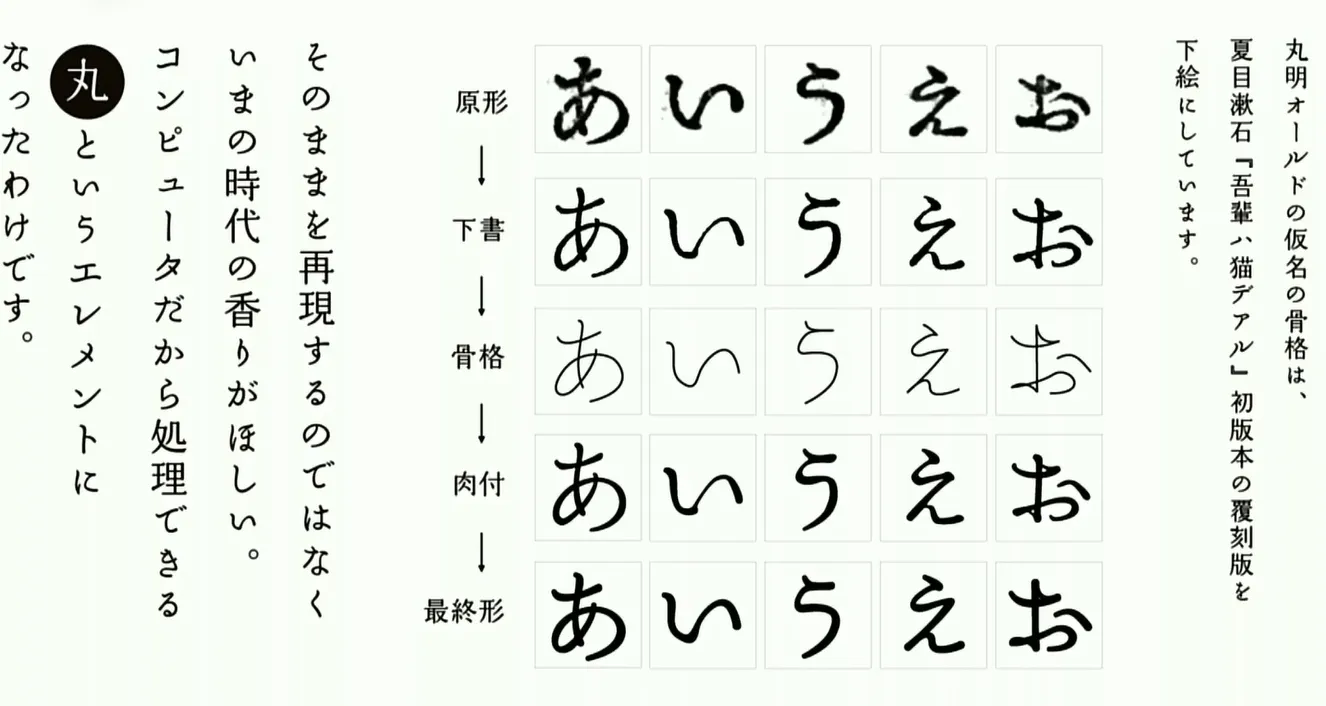
「丸明オールド」は口に入れるものや肌に触れるものなど、柔らかい印象を持たせたい時に使われている印象があります。アナログの時代は、丸はコンパスで書かなければいけなかったそう。そのため書体に取り入れようとしても線と円の重なるところに違和感が生じてしまったのですが、パソコンの誕生でスムーズに描くことが可能となりました。広告を長くやっていたことでオリジナリティを求める癖がつき、明朝体と丸を組み合わせてみようかなというアイディアになったそうです! 軽くなりすぎないよう字形はオーソドックスを保ち、夏目漱石「吾輩ハ猫デアル」初版本の復刻版を下絵にしたとのこと。常識にとらわれない、片岡さんらしい「丸明オールド」が2000年に誕生しました。
「書体デザイナー・木龍歩美」の誕生ヒストリー
続いては、木龍さんのお話です。「昔から文字に強い興味があったというわけではないですが、父が歴史資料館で学芸員をしていた影響で崩し字や活字の書物は読めていました。父が絵や文字を書くことが好きだったので、幼いころからデザインに触れる機会は多かったのかも」と話す木龍さん。書体デザイナーとしてのセンスはこの頃の経験が影響していたのですね。タイポグラフィに触れたのは大学に入ってからだそう。文字を組むことだけで表現ができることに衝撃を受け、文字を使った立体アート作品を作ることが楽しくなったとお話くださいました。
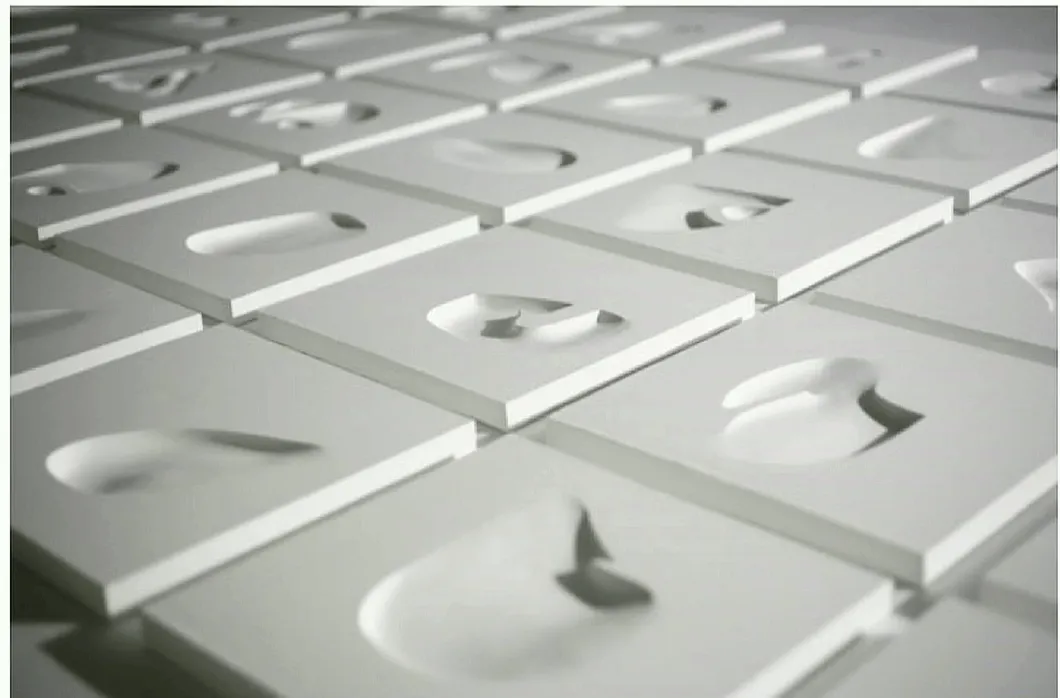
上の写真は木龍さんの卒業制作作品です。この作品は、ひらがなの余白を立体化したものだそうです。木龍さんの書体「きりこ」のもとはこの頃からすでに誕生していたんですね……!
木龍さんは幼い頃から書体やデザインに触れており、それが自然と自分の興味となって今に繋がっていたので、体験したことは経験となり自分自身を形成していくのだなと改めて感じました。
木龍さんは砧書体制作所へ入社当時、丸丸ゴシックの印象から可愛らしい方が制作されているのかなと思って事務所を訪れたそうなのですが、思いもよらず重厚感のある片岡さんが出てきて驚いたとお話していました。片岡さんも木龍さんが少し退いたのがわかったのだとか(笑)。しかしそれ以上に驚いたのが、あれだけの書体をたった一人で制作していたということ。一緒に働くと片岡さんのスピード感は目を見張るものがあり、木龍さんもお手本にしているとおっしゃっていました。10年間一人で書体デザインをしていた片岡さんが木龍さんを採用した理由は、卒業制作を見てここまでやりきるなら文字もできるだろうと感じたのだとか。数年もの時間を要する書体制作をお二人だけで続けていることにパワーを感じました。
お二人の軌跡を辿ると、その方々が作る書体にさらに興味がわきとても楽しい時間でした! 普段何気なく使用していたフォントも、物語を知ると愛着が沸いてきますね。
開発中の新書体「未来Font“魁”」
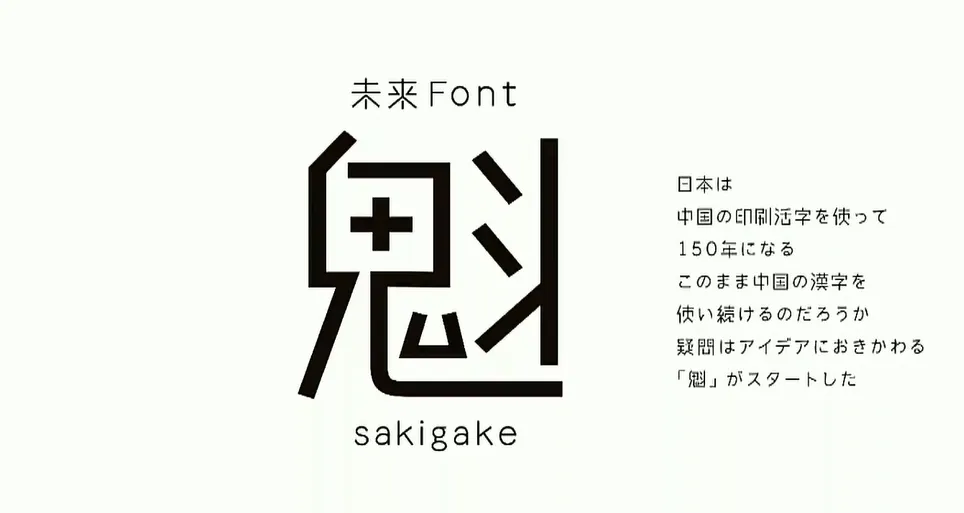
未来Font「魁」(さきがけ)は、中国で生まれた漢字が今後日本独自の「さきがけ」の漢字として変化していくとしたらどうなるのだろうかと考えたことから生まれた砧書体制作所の開発中の新書体です。もとの漢字が連想できるギリギリのところまで省略した、個性溢れる書体となっています。フォントのデータ量を軽くする目的も含んでいるのだとか。こんな略し方をするのか!と、楽しんで見てほしいとのこと。漢字が特徴的なため平仮名は主張を強くせずオーソドックスにし、手書きの右肩上がりを反映させることで読みやすさや親しみやすさを表現したそうです。新鮮な本文組がおもしろいですね。開発中の「魁」完成が今から待ち遠しいです!
魁の開発秘話の中で印象的だったのが、「魁のような実験的なものは、書体を作る人からすると読めないとかフォントって言えるのとなるが、それはあえて言ってもらった方がいい。そのほうがフォントってなんなの?と意識する人が広がる。本来はもっと日本語フォントの在り方をみんなで意識して話し合うべきであって、フォントは人間がいろいろ考えて作られている訳だから、まずは気軽にみんなにぶつけてみようかなと思った」という片岡さんのお言葉。フォントの可能性を追求し、フォントを愛しているからこその言葉に感じました。仕事に愛があるって素晴らしいです……!
次世代のフォント技術「バリアブルフォント」
バリアブルフォントは、2016年9月にApple、Google、Microsoft、Adobeが共同発表しました。サイズやウェイト、字幅など形を変えることことができフォントのさらなる可能性を感じさせますが、制作に時間がかかることがデザイナーとしては懸念点に。しかし一文やアイコンとしての提案もあるのではと試行錯誤で制作してみたそう。フォントってこんな表現もできるのかと楽しいデザインがたくさん出てきて、枠にとらわれず新しいことを取り入れていく砧書体制作所らしさを感じました。
そしてイベントの中では木龍さんの新しい屋号「ムーロンタイプ」のご紹介も。木龍さんの新たな門出に今後の活動が楽しみです!
この対談で新たなことに挑戦する力がどんどん加速しているように感じた砧書体制作所に益々目が離せません!